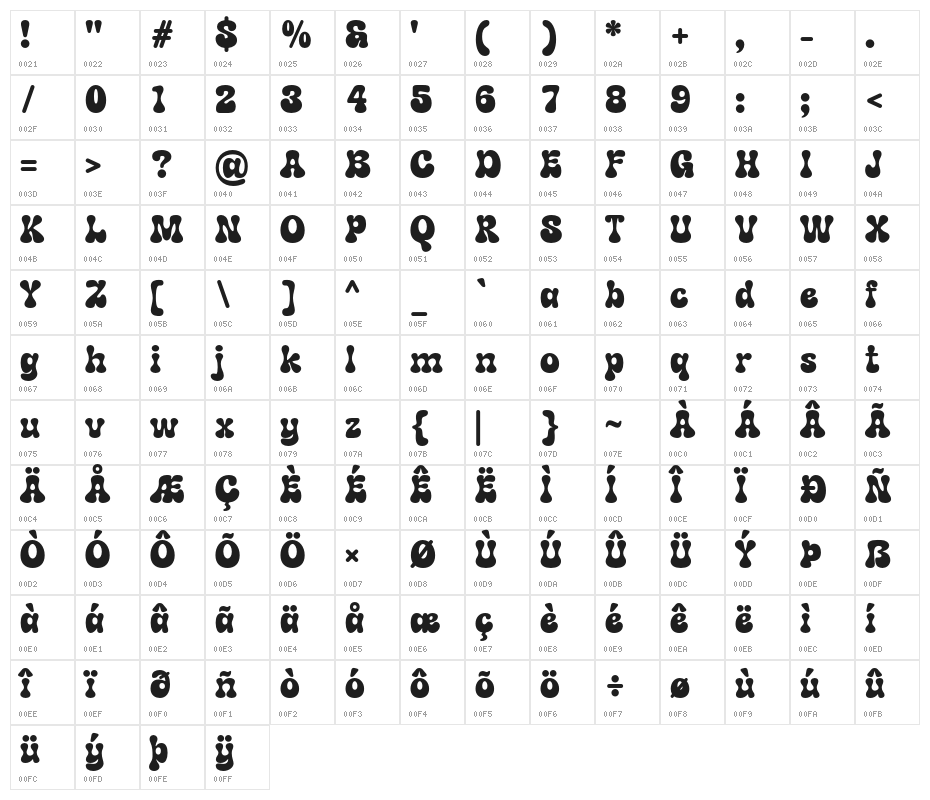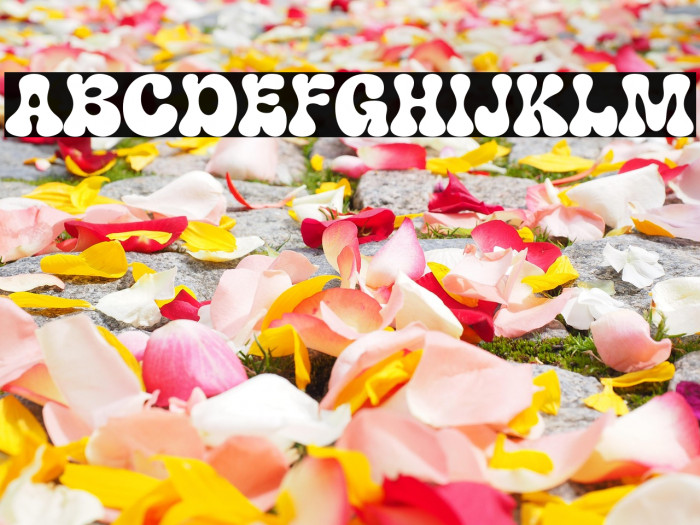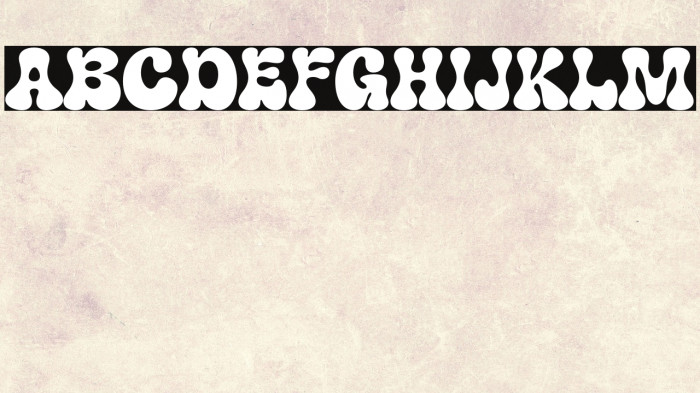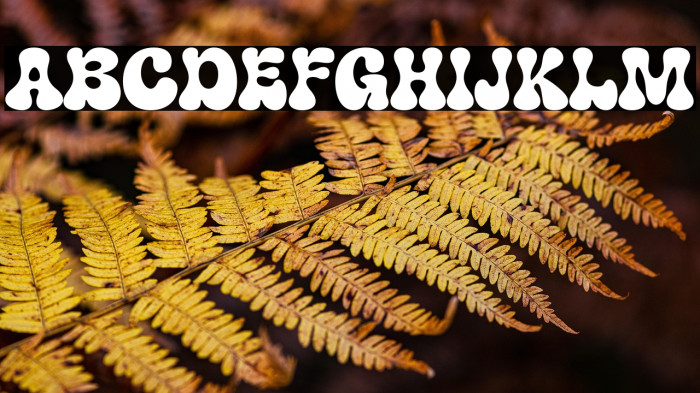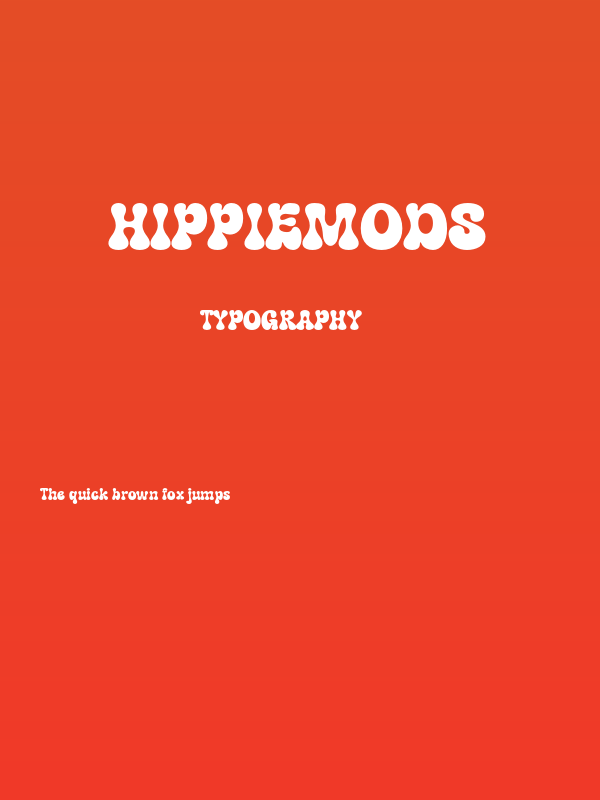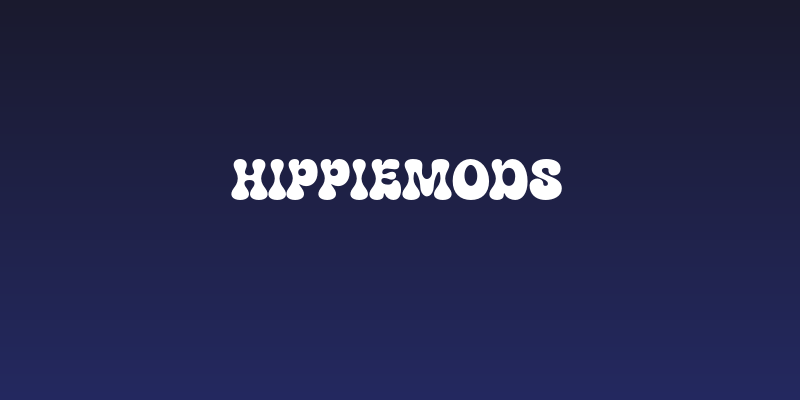
HippieMods Font
| 分类 | Kids |
| 整体风格 | Vintage |
| 推荐项目 | Ideal for retro-themed posters, children's book covers, playful branding, and event invitations. |